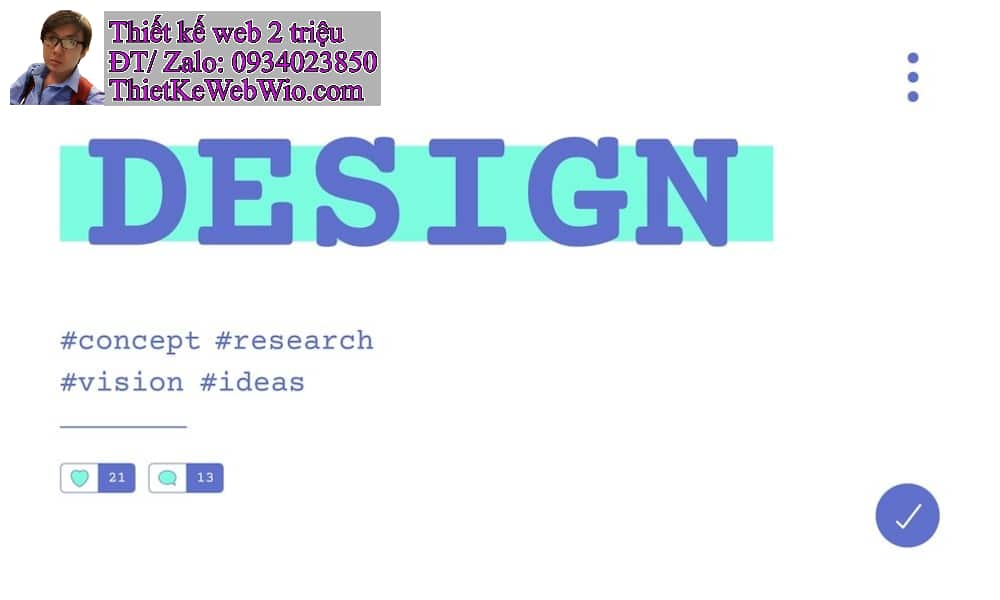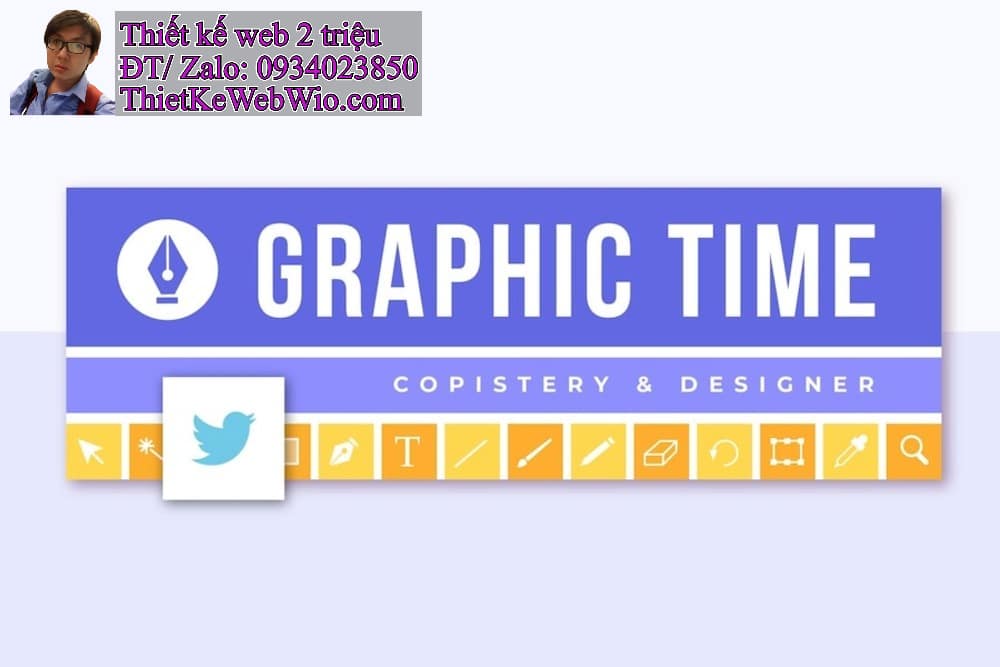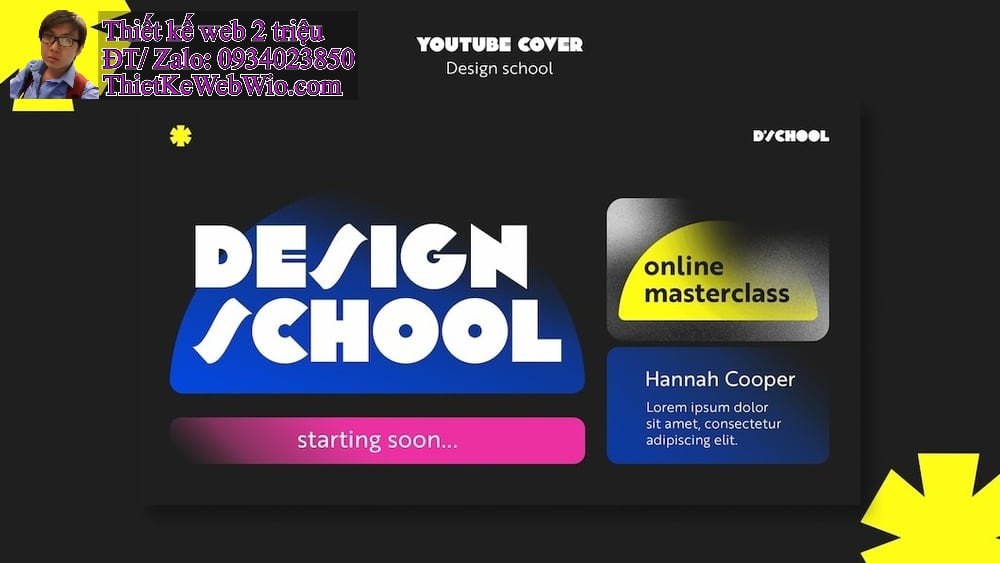
Trong thế giới thiết kế website, font chữ không chỉ là một phần nhỏ, mà còn là yếu tố quan trọng giúp truyền tải thông điệp, tạo dấu ấn thương hiệu và tối ưu hóa trải nghiệm người dùng. Một font chữ trong thiết kế web chuyên nghiệp không chỉ cần bố cục đẹp, hình ảnh sắc nét mà còn cần sử dụng font chữ phù hợp để tạo nên sự hài hòa và hiệu quả.
Hãy cùng tìm hiểu chi tiết về dịch vụ font chữ trong thiết kế web, lý do tại sao font chữ lại quan trọng và cách chọn font chữ phù hợp để tối ưu hóa website của bạn.
Font Chữ Là Gì Và Tầm Quan Trọng Của Nó Trong font chữ trong thiết kế web
Font chữ là tập hợp các ký tự chữ cái, số và ký hiệu được thiết kế với phong cách cụ thể. Trong thiết kế web, font chữ đóng vai trò như một kênh giao tiếp thị giác giữa font chữ trong thiết kế web và người dùng.
Tầm quan trọng của font chữ:
- Truyền tải thông điệp: Font chữ thể hiện cảm xúc, tính cách thương hiệu, từ đó giúp thông điệp của website được truyền tải rõ ràng hơn.
- Tăng tính thẩm mỹ: Một website với font chữ được thiết kế tốt sẽ thu hút người xem và giữ chân họ lâu hơn.
- Cải thiện trải nghiệm người dùng (UX): Font chữ dễ đọc, kích thước phù hợp giúp người dùng lướt font chữ trong thiết kế web dễ dàng mà không cảm thấy khó chịu.
- Tối ưu hóa SEO: Font chữ rõ ràng và tương thích trên nhiều thiết bị giúp tăng khả năng truy cập, từ đó cải thiện thứ hạng website trên các công cụ tìm kiếm.
Các font chữ trong thiết kế web Phổ Biến
Hiện nay, font chữ được chia thành nhiều loại khác nhau, mỗi loại có ưu điểm riêng phù hợp với từng mục đích sử dụng. Dưới đây là các nhóm font chữ phổ biến:
Serif (Chữ có chân)
- Đặc điểm: Có các đường gạch nhỏ (chân) ở đầu hoặc cuối các ký tự.
- Ứng dụng: Thường dùng trong các font chữ trong thiết kế web truyền thống, lịch lãm như tạp chí, báo chí, hoặc các lĩnh vực như luật, giáo dục.
- Ví dụ: Times New Roman, Georgia.
Sans-serif (Chữ không chân)
- Đặc điểm: Font chữ tối giản, không có chân, mang lại cảm giác hiện đại.
- Ứng dụng: Phù hợp với các font chữ trong thiết kế web công nghệ, startup, thương mại điện tử.
- Ví dụ: Arial, Helvetica, Open Sans.
Script (Chữ viết tay)
- Đặc điểm: Mềm mại, uốn lượn như chữ viết tay, thường mang tính chất nghệ thuật.
- Ứng dụng: Dùng trong các website sáng tạo, thời trang hoặc dịch vụ cưới.
- Ví dụ: Pacifico, Lobster.
Monospace (Chữ đơn cách)
- Đặc điểm: Mỗi ký tự có cùng chiều rộng, tạo cảm giác cổ điển và kỹ thuật.
- Ứng dụng: Dùng trong font chữ trong thiết kế web lập trình, công nghệ.
- Ví dụ: Courier New, Consolas.
Display (Chữ trang trí)
- Đặc điểm: Phong cách độc đáo, được thiết kế riêng để gây ấn tượng mạnh.
- Ứng dụng: Thường dùng trong tiêu đề hoặc logo.
- Ví dụ: Impact, Bebas Neue.
Các Yếu Tố Cần Xem Xét Khi Lựa Chọn font chữ trong thiết kế web
Phù hợp với thương hiệu
- Font chữ nên phản ánh đúng tính cách và giá trị cốt lõi của thương hiệu.
- Ví dụ: Một thương hiệu cao cấp nên chọn font chữ serif để thể hiện sự sang trọng.
Tính dễ đọc
- font chữ trong thiết kế web cần dễ đọc trên mọi thiết bị và kích thước màn hình.
- Tránh các font quá phức tạp khiến người dùng khó nắm bắt nội dung.
. Độ tương thích
- Font chữ phải hiển thị tốt trên mọi trình duyệt web và hệ điều hành.
Hỗ trợ ngôn ngữ
- Đảm bảo font chữ hỗ trợ đầy đủ các ký tự tiếng Việt có dấu.
Tốc độ tải trang
- Các font chữ trong thiết kế web quá nặng có thể làm chậm tốc độ tải trang. Cần tối ưu hóa font chữ bằng cách sử dụng các định dạng như WOFF, WOFF2.
Dịch Vụ font chữ trong thiết kế web Chuyên Nghiệp
Khi sử dụng dịch vụ font chữ trong thiết kế web chuyên nghiệp, font chữ luôn được tối ưu hóa để mang lại hiệu quả tốt nhất. Các dịch vụ bao gồm:
Tư vấn và lựa chọn font chữ
- Đội ngũ chuyên gia font chữ trong thiết kế web sẽ phân tích thương hiệu và khách hàng mục tiêu để đưa ra lựa chọn font chữ phù hợp.
Tùy chỉnh font chữ
- Tạo font chữ riêng biệt để thể hiện cá tính thương hiệu.
Tối ưu hóa font chữ
- font chữ trong thiết kế web Nén file font để giảm dung lượng mà vẫn giữ được chất lượng hiển thị.
Tích hợp font chữ từ thư viện trực tuyến
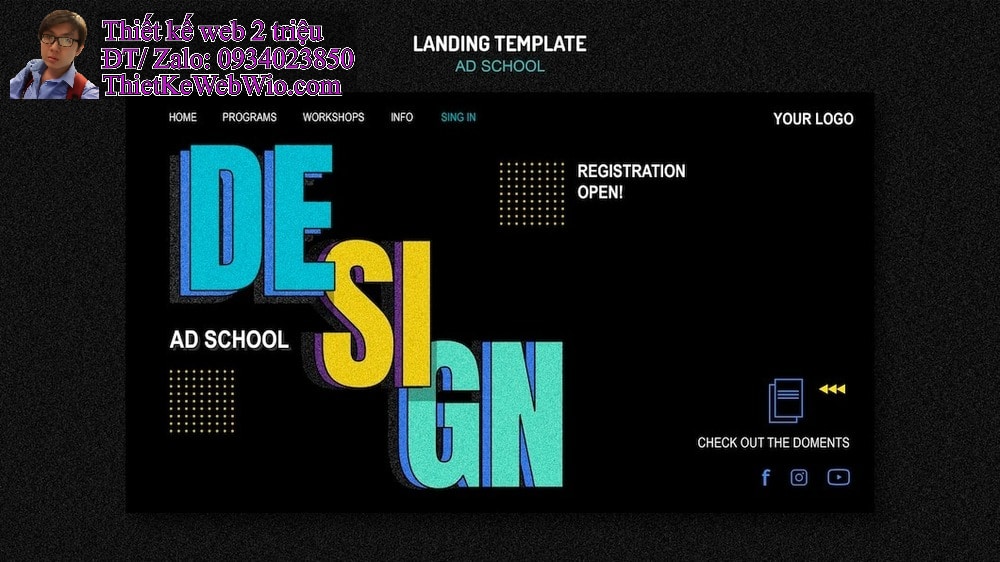
font chữ trong thiết kế web là một yếu tố không thể thiếu để tạo nên một website ấn tượng và hiệu quả. Việc lựa chọn font chữ phù hợp không chỉ giúp truyền tải thông điệp của thương hiệu mà còn tạo nên sự khác biệt so với đối thủ cạnh tranh.